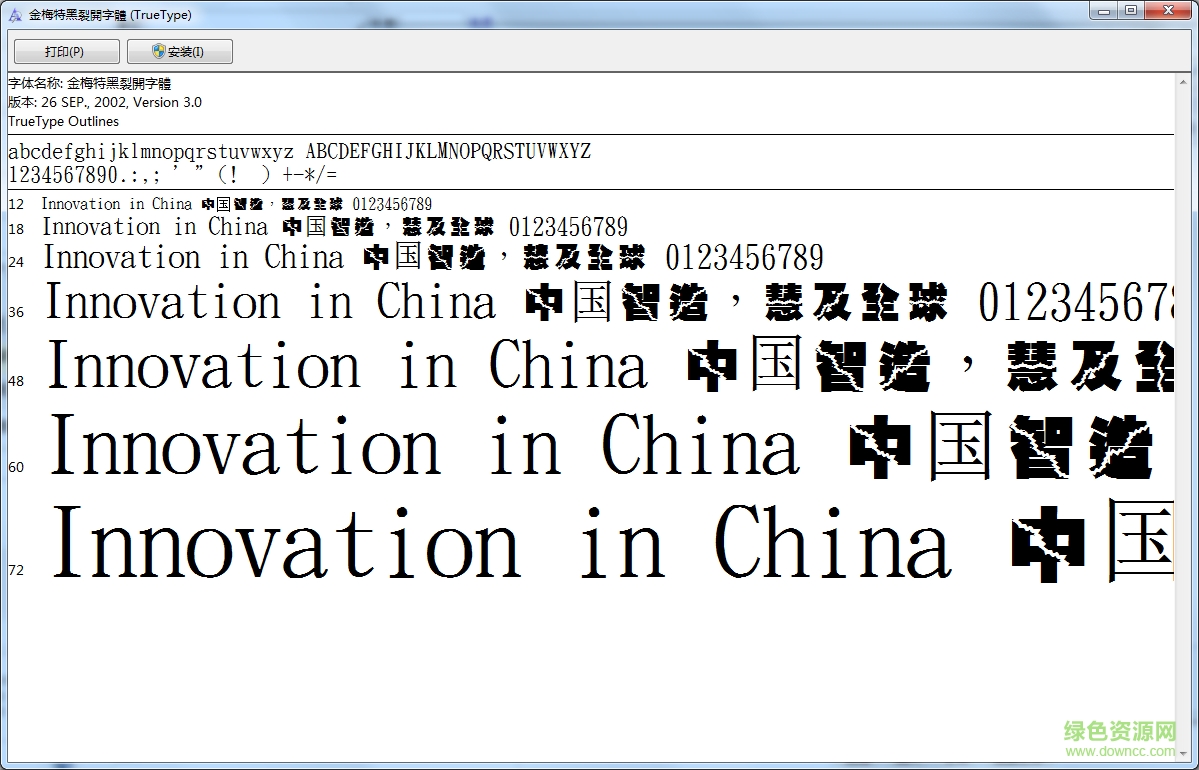
金梅特黑裂開體字體是一款非常實(shí)用的金梅藝術(shù)字體,字體比較的粗,有一種裂開的效果,非常的具有藝術(shù)氣息,看著十分的霸氣,支持中英文,歡迎有需要的朋友到綠色資源網(wǎng)下載使用!
金梅特黑裂開體繁是一款超黑的藝術(shù)字體,繼承了金梅系列字體的風(fēng)格,每個(gè)字都像被閃電劈過似的,十分具有藝術(shù)感,可以應(yīng)用于廣告設(shè)計(jì)、平面設(shè)計(jì)、印刷包裝、藝術(shù)設(shè)計(jì)、網(wǎng)站設(shè)計(jì)領(lǐng)域。